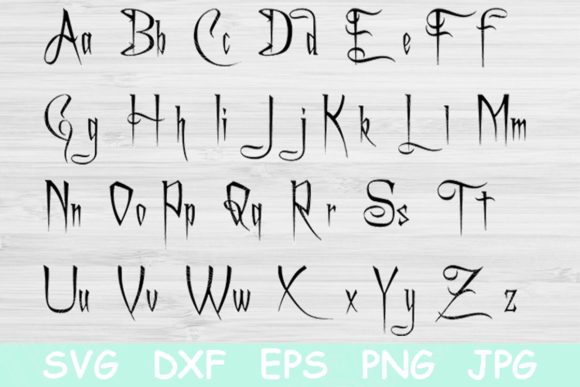
Letter Fonts Svg Script Vine Digitial.
Encontrar los elementos de diseño adecuados puede ser un desafío, pero Letter Fonts Svg Script Vine Digitial. ofrece una colección excepcional que eleva tu trabajo al instante.
Ya sea que estés creando productos POD (impresión bajo demanda), invitaciones de boda o gráficos para redes sociales, Letter Fonts Svg Script Vine Digitial. es una opción ideal.